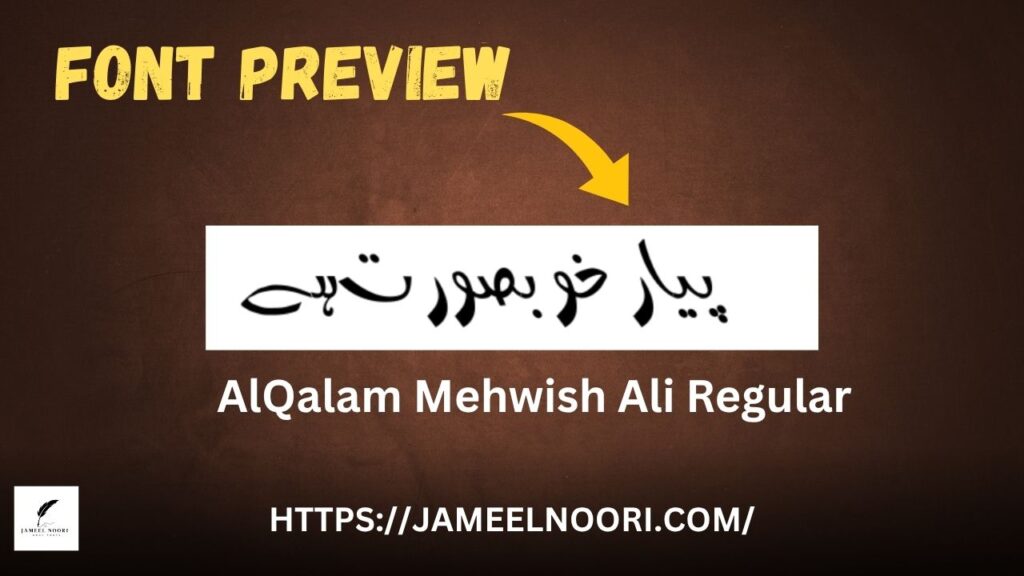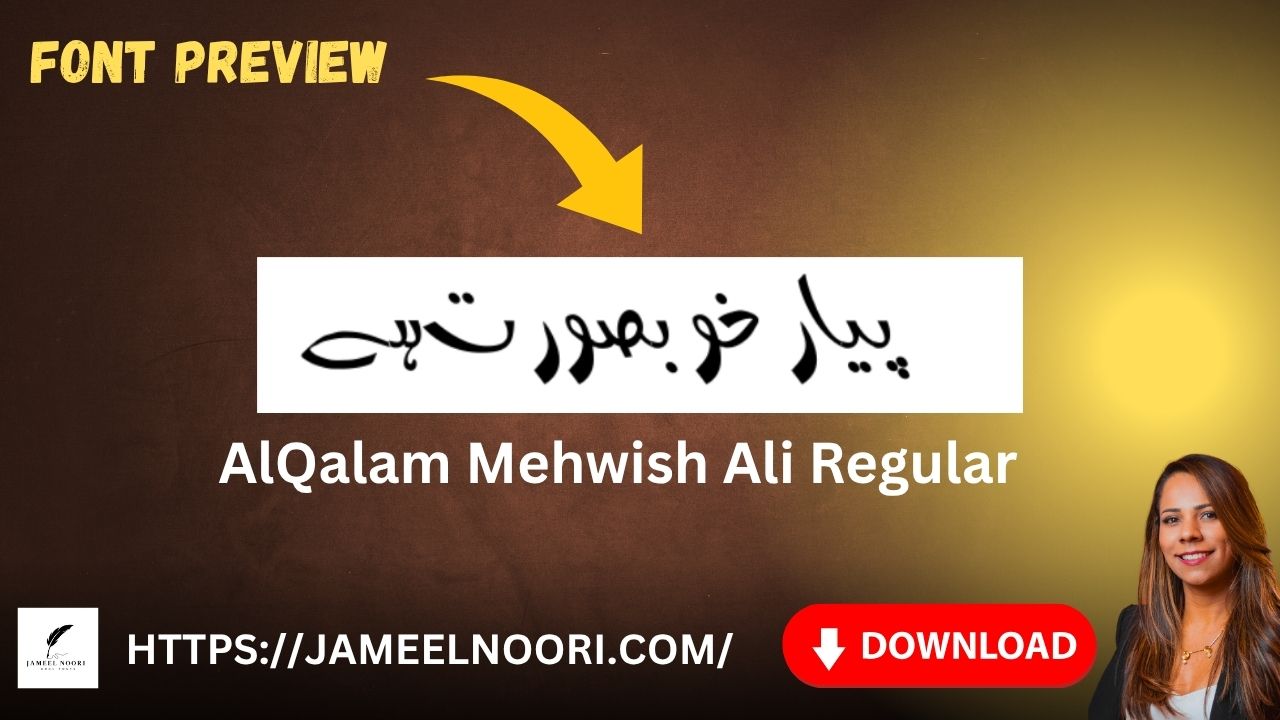
Introduction to Urdu Font AlQalam Mehwish Ali
Urdu Font AlQalam Mehwish Ali ek bohat hi khubsurat aur professional Urdu typeface hai jo specially Urdu designers aur writers ke liye design kiya gaya hai. Ye font apne clean aur elegant style ki wajah se Pakistan mein bohat zyada popular hai. Is font ko AlQalam Mehwish Ali Regular ke naam se bhi jaana jata hai aur ye TrueType format mein available hai.
Features of Urdu Font AlQalam Mehwish Ali
Ye font Urdu writing ke liye perfect hai, aur iska design aesthetically balanced hai. Niche kuch important features diye gaye hain:
- Clean aur professional design
- Urdu calligraphy style font
Why Choose Urdu Font AlQalam Mehwish Ali?
Is font ka biggest advantage uska beautiful Urdu script aur ease of readability hai. Designers aur Urdu content creators ke liye ye ek best choice hai.
Agar aap apne Urdu documents ya graphics me modern aur elegant touch lana chahte hain, to ye font ultimate solution hai.
Comparison Table: AlQalam Mehwish Ali vs Other Urdu Fonts
| Feature | AlQalam Mehwish Ali | Jameel Noori Nastaleeq | AlQalam Taj Nastaleeq |
| Type | Regular TrueType | Nastaleeq Script | Nastaleeq Script |
Agar aap Urdu content likhne, design karne, ya print ready documents banane ke shaukeen hain to Urdu Font AlQalam Mehwish Ali aapke liye ek affordable aur expert choice hai. Iska elegant look aur professional appeal aapke Urdu projects ko next level par le jaata hai.
What is Urdu Font AlQalam Mehwish Ali?
It is a beautiful Urdu TrueType font designed for professional writing and design purposes.
Does it support Urdu calligraphy style?
Yes, this font is designed with an elegant Urdu calligraphic touch.
What makes it better than other Urdu fonts?
Its high readability, aesthetic beauty, and lightweight design make it superior.
Can I use it for logo or poster design?
Yes, it’s ideal for Urdu posters, banners, and logos.